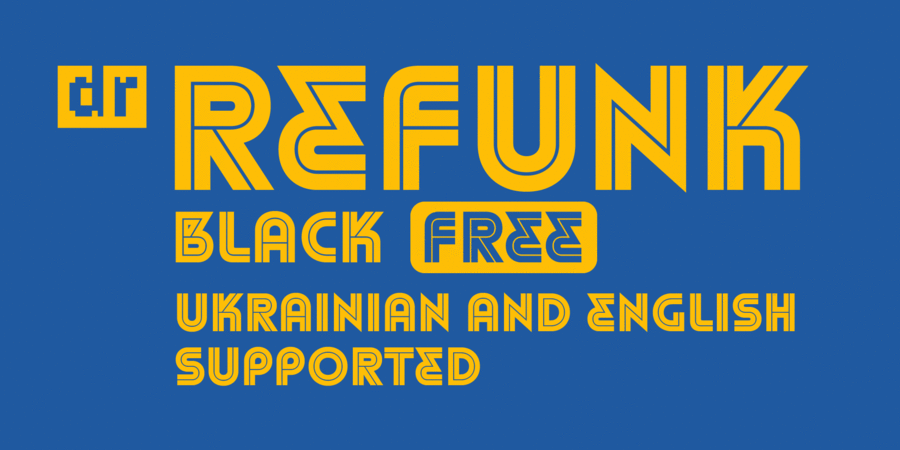
Опис шрифта DR Refunk FREEDR Refunk Black Free – це смугастий геометричний шрифт у традиціях модернізму. Безкоштовна версія DR Refunk з підтримкою англійської та української. Вільна ліцензія CC BY-ND 4.0 для комерційного та некомерційного використання. Шрифт розробив Дмитро Растворцев у 2023 році.
Особливості сімейства шрифтів DR Refunk FREEХіт десятиліття:
Хіт 1930-х Хіт 1970-х Хіт 1980-х DR Refunk FREE підтримує 2 мовиФункції сімейства шрифтів DR Refunk FREEЗастосування гарнітури у верстці:
Асоціації з сімейством шрифтів DR Refunk FREEОсобистість і характер гарнітури:
сильний, важкий, гучний, модний, оригінальний, виразний, якісний, дзвінкий, позитивний, артистичний, сучасний, міський, музичний, популярний, точний, свіжий, твердий, чіткий, яскравий, помітний, мотивуючий, архітектурний, хіпстерський, святковий, радісний, рівний, неоновий, клубний, молодіжний, сексуальний, манірний, дотепний, грайливий, глянцевий, тусовочний, ритмічний, привабливий, танцювальний, нічний, пульсуючий, мерехтливий, гострий, колючий, електронний, різкий